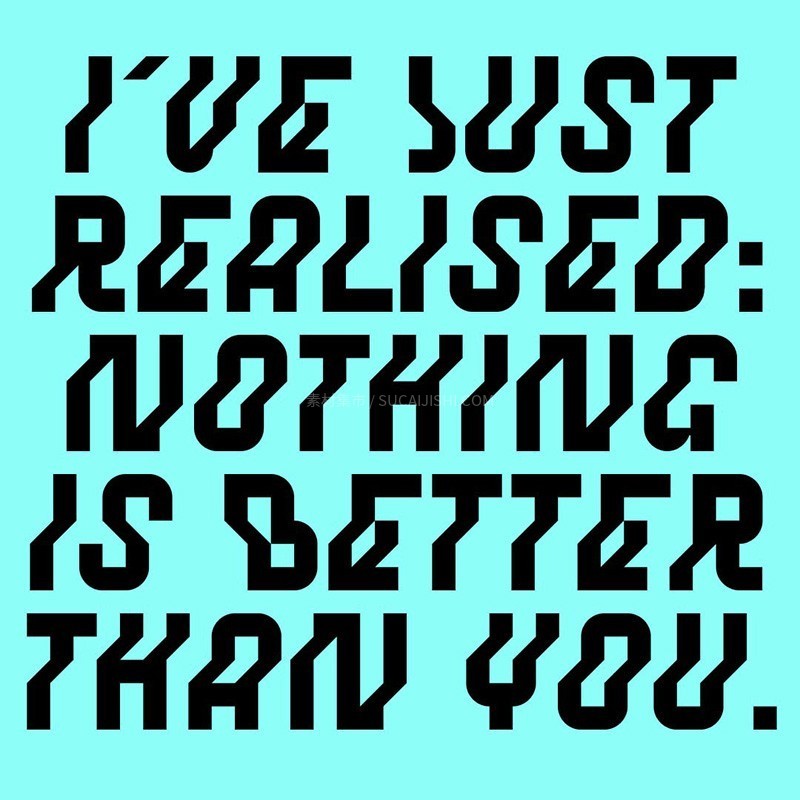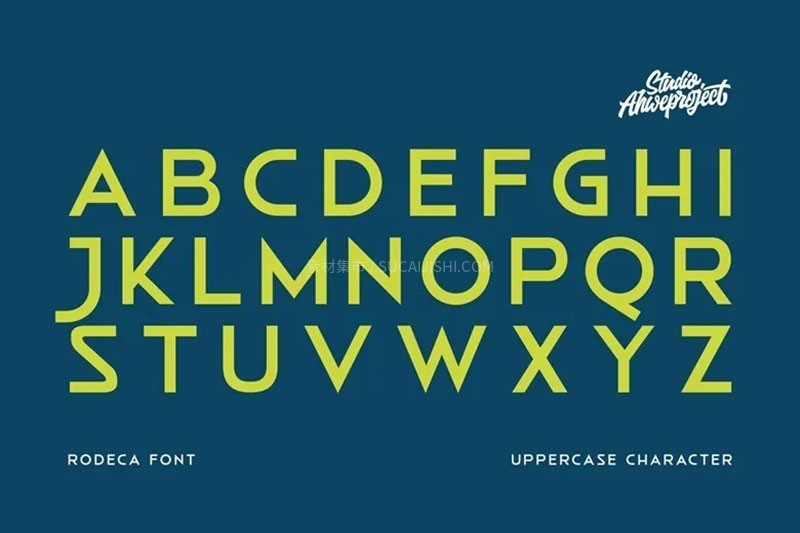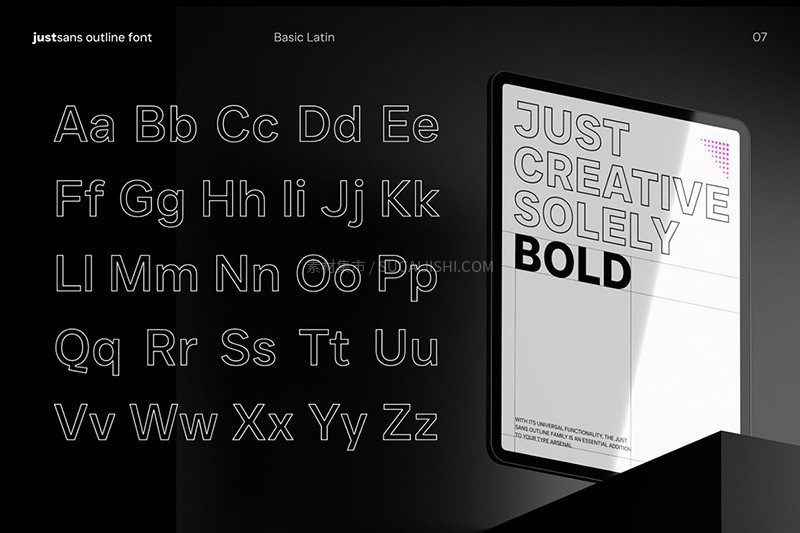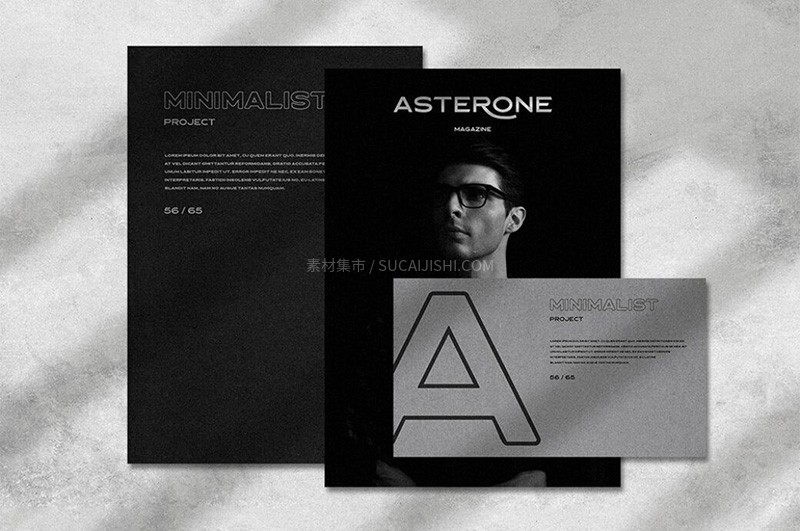
6款轮廓线条英文字体合集
这套精选的轮廓线条字体合集,专为打造现代、时尚的设计作品而生。每款字体都拥有独特的轮廓线条美感,非常适合用于制作时尚海报、品牌标志、标题设计和艺术插画,让您的作品更具视觉冲击力和设计感。
JUST Sans OUTLINE
UST Sans Outline 以其独特的空心线框风格脱颖而出。它融合了几何感、现代极简主义和基于笔触的线性特点,巧妙地增强了视觉深度和对比度。
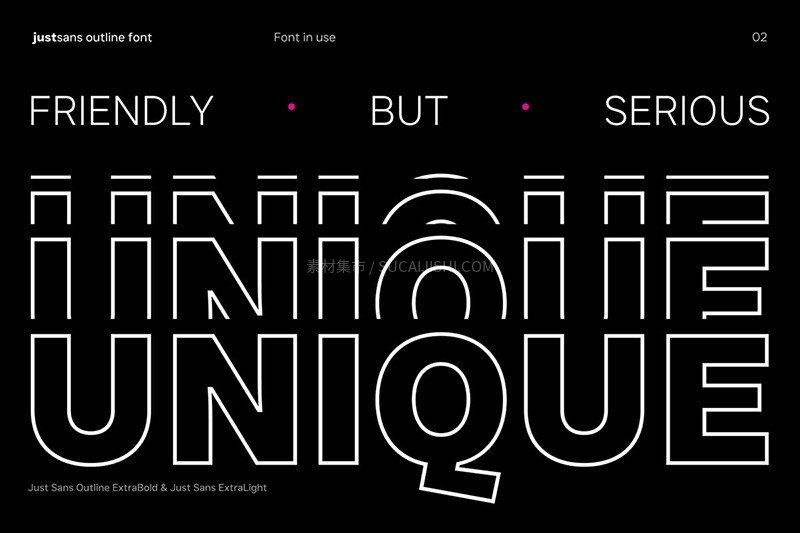
Asterone
Asterone 是一款现代字体,非常适合用于标题、标识、服装、邀请函、品牌推广、包装、广告等多种用途。
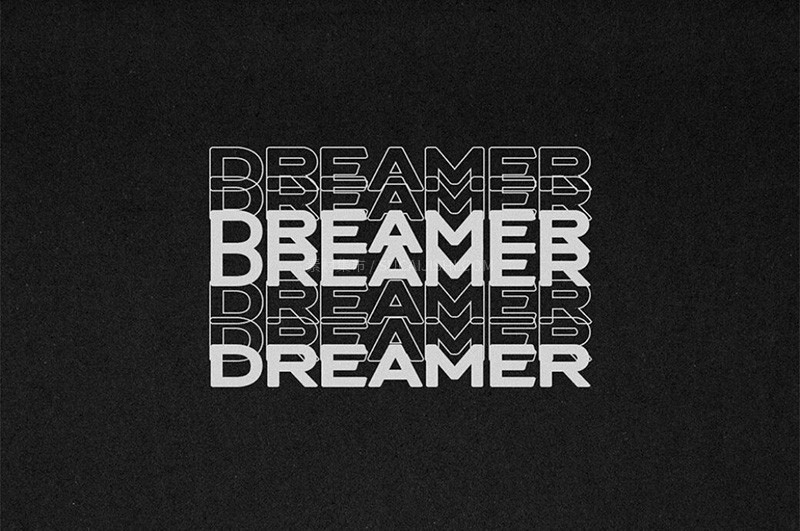
Drabina
一款兼具粗体几何力量感和三维灵动性的独特字体。它大胆地去除了上行和下行部分,形成了紧凑且现代的布局。该字体支持基本的西里尔字母和拉丁字母,满足不同语言的设计需求。您可以在实心(Solid)和空心(Outline)两种风格之间选择,轻松打造出具有辨识度和艺术感的标题、标志或图形元素。
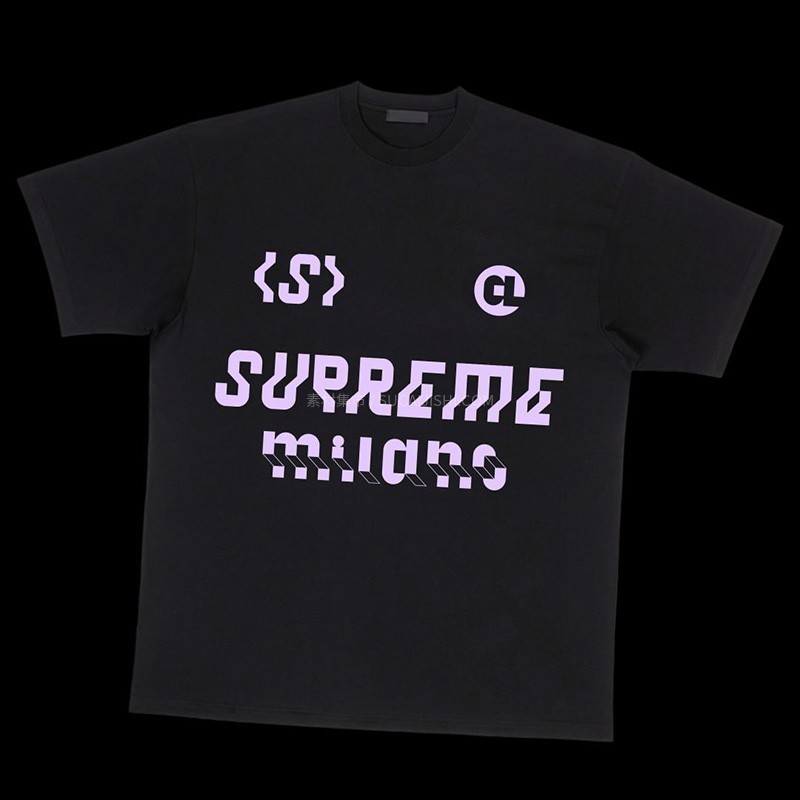
Florisa
Florisa 字体的设计灵感源自花瓣的独特形状,并被制成独特的字母。Florisa 可用于展示、标题、徽标等。Florisa 包含大写字母、数字和一些符号,以及行距版本。
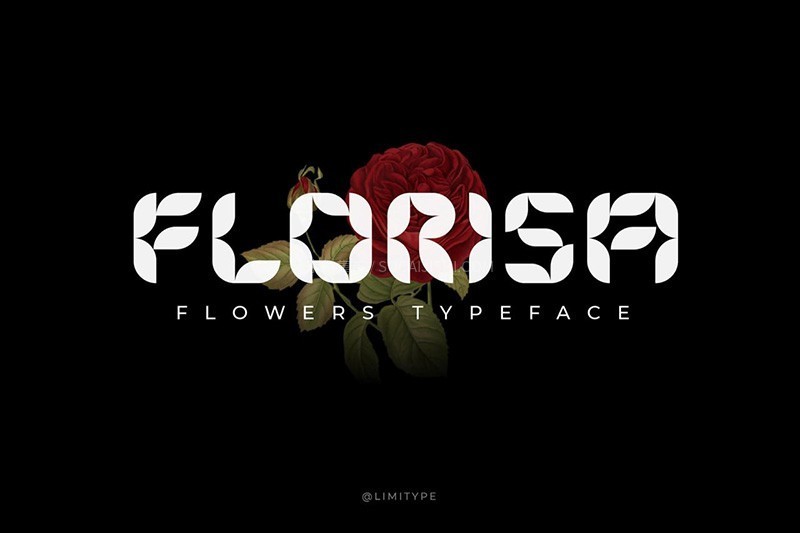
Goose Buster
Goose Buster 字体拥有三种独特风格——常规、印花和轮廓,每一种都散发着迷人的复古魅力。
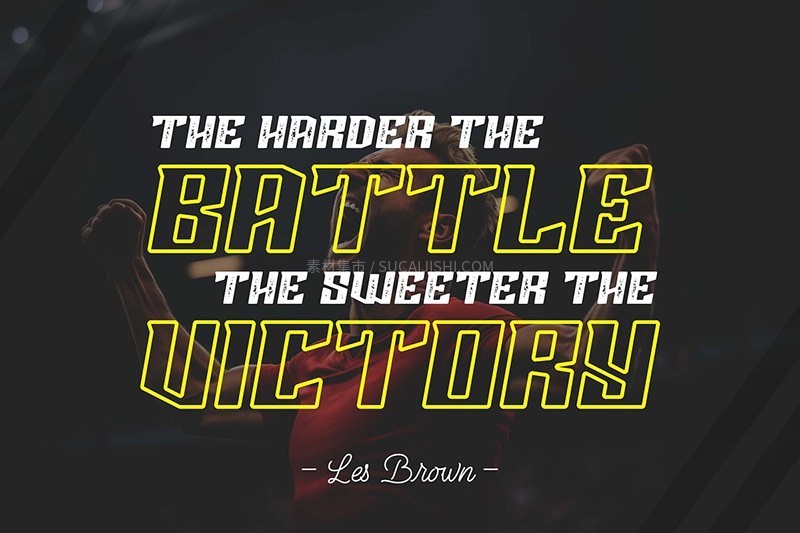
Rodeca
这款现代无衬线字体将经典几何图形与时尚现代的格调融为一体,带您领略装饰艺术时代的大胆优雅。Rodeca 拥有 5 种独特的字重、丰富的连字和替代字体,能够满足您的多功能设计需求,为品牌设计、编辑排版、海报、徽标设计和奢华包装等项目注入独特的艺术魅力。